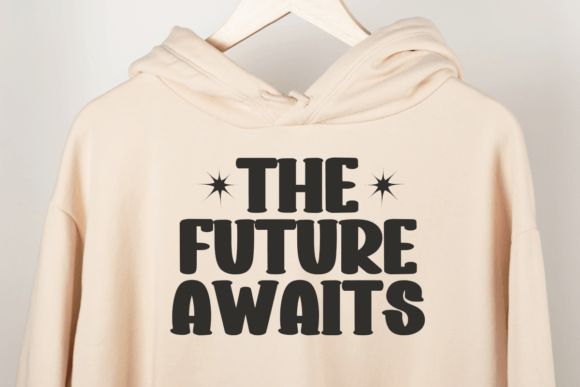
Hello Thick Font
Hello Thick Font هو خط عصري وجريء يتميز بحروف سميكة وأنيقة، مما يجعله مثاليًا للتصميمات القوية والجذابة. سواء كنت تعمل على الشعارات، العناوين البارزة، المنشورات على وسائل التواصل الاجتماعي، أو التصاميم الإعلانية، فإن هذا الخط سيضيف لمسة من التميز والاحترافية إلى مشاريعك.
يتميز Hello Thick Font بتناسق رائع وسهولة في القراءة، مما يجعله خيارًا مثاليًا للمبدعين والمصممين الذين يبحثون عن خط يجمع بين الحداثة والتأثير البصري القوي. قم بتحميله الآن وأضف لمسة من الإبداع إلى أعمالك! ????✨